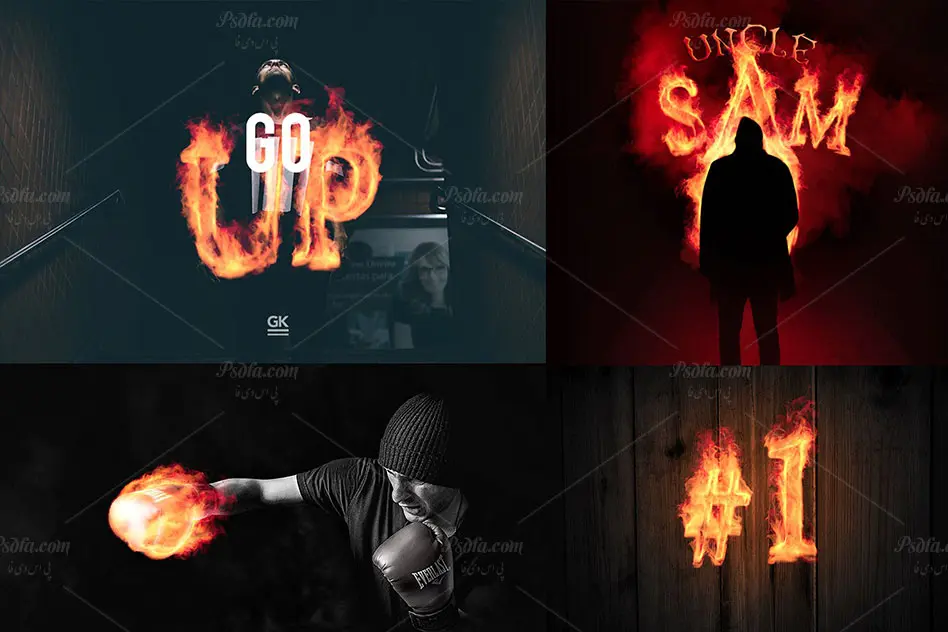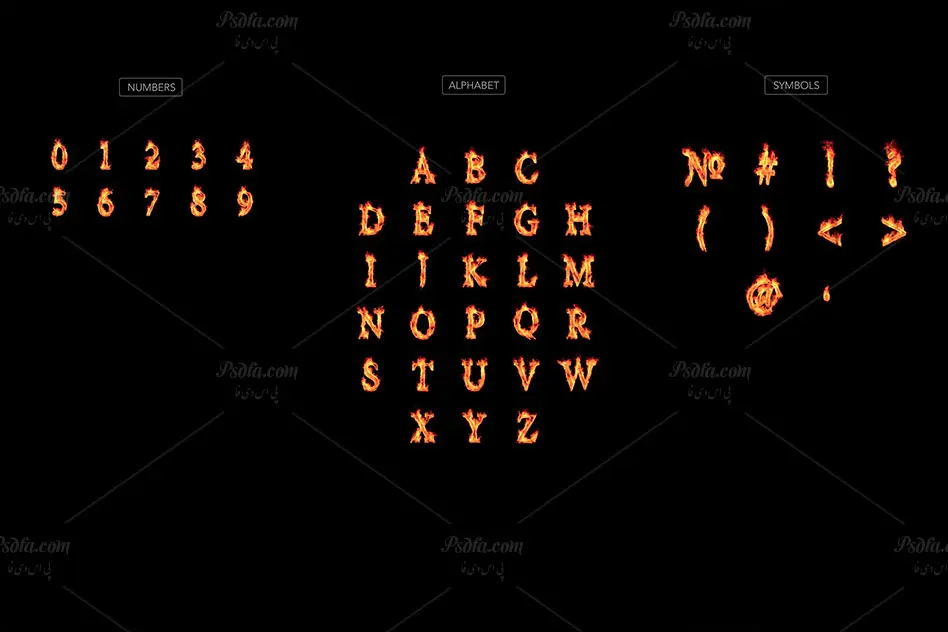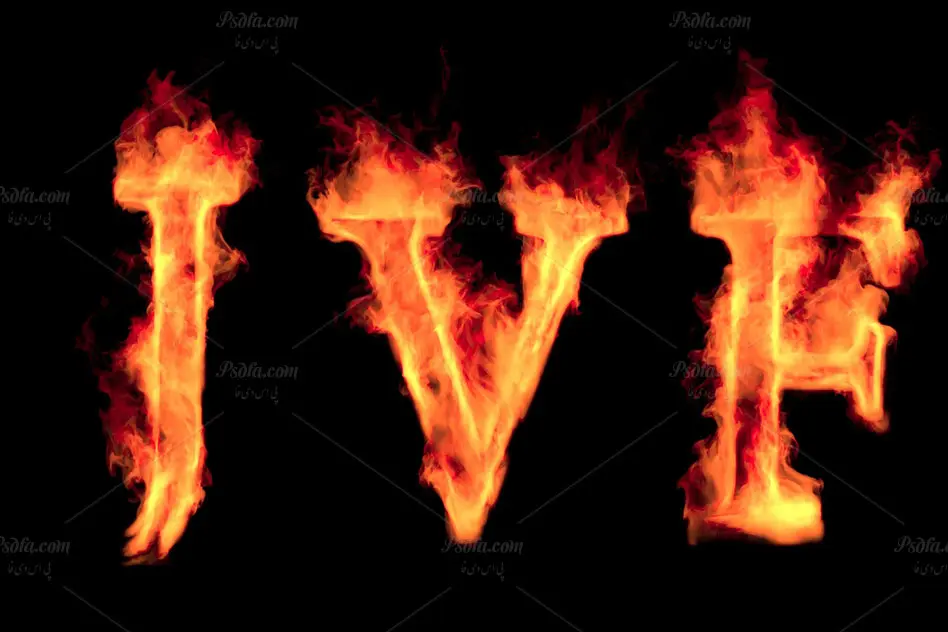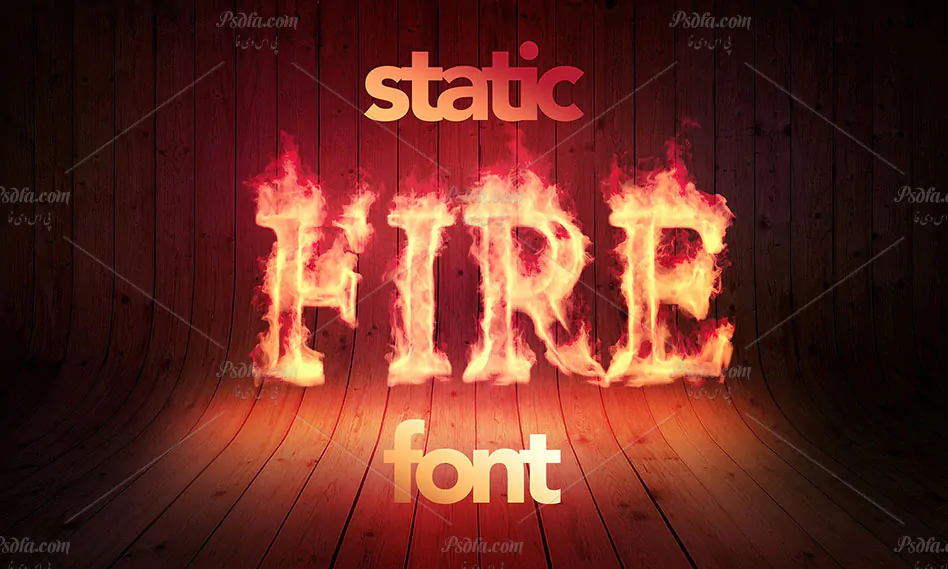
در این مطلب شاهد فونت آتشین – مجموعه کاراکترهای حروف و اعداد انگلیسی با افکت آتشین مناسب جهت استفاده در نرم افزار فتوشاپ می باشید. این مجموعه کاراکتر در قالب 3 فایل psd قرار گرفته اند که به کمک آن ها و یا از قرار دادن آن ها در کنار یکدیگر می توانید طرح های آتشین فوق العاده زیبایی ایجاد کنید. فایل ها از کیفیت بالایی برخوردار بوده و دارای سایز و ابعاد 1200 × 1200 پیکسل هستند و مناسب جهت ایجاد طرح هایی با رزولوشن بالا می باشند. همچنین شما می توانید تمام کاراکتر ها را به صورت png بدون بک گراند در فایل های مجزا ذخیره نموده و از آن ها در طرح های خود استفاده کنید.